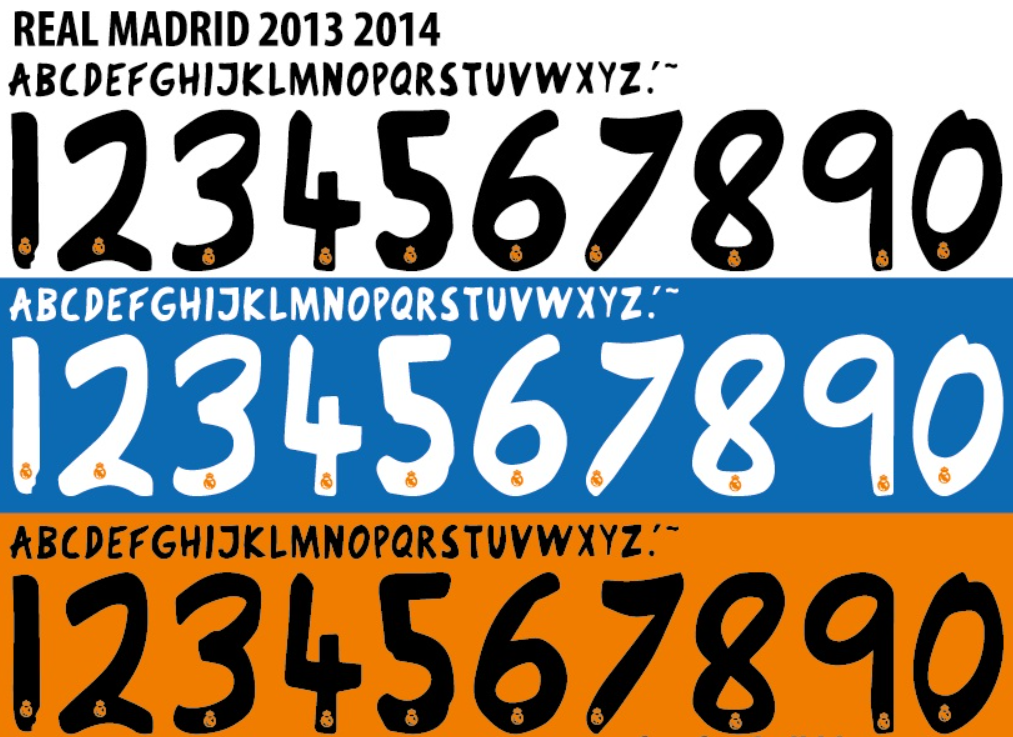
Poucas camisas pesam tanto na história do futebol quanto o uniforme usado pelo Real Madrid na temporada 2013/2014. Foi com essa tipografia nas costas que o clube merengue, sob o comando de Carlo Ancelotti, conquistou a tão sonhada “La Décima” Champions League em Lisboa.
Se você quer recriar a magia daquela final lendária ou personalizar camisas com o estilo usado por ídolos como Cristiano Ronaldo, Sergio Ramos e Gareth Bale, este é o arquivo definitivo. A Adidas entregou um design único naquele ano, e agora você pode tê-lo em seu computador.
Estilo Visual e Identidade
A fonte de 2013-2014 foge completamente do padrão “blocado” e rígido que a Adidas costumava aplicar em anos anteriores. Ela apresenta um design mais fluido e orgânico, quase simulando uma escrita manual estilizada, mas mantendo a legibilidade necessária para o esporte.
Este estilo visual casou perfeitamente com os detalhes em laranja e cinza da camisa titular daquela temporada. É uma tipografia que transmite movimento e modernidade, eternizada no momento do gol de empate de Sergio Ramos aos 93 minutos. É perfeita para estampas retrô e homenagens a uma das melhores épocas do futebol espanhol.
Dica de Uso: Para um acabamento 100% fiel à camisa de jogo (Match Worn), lembre-se de incluir o escudo do clube em miniatura na base dos números, caso seu software de edição permita a inserção de vetores.